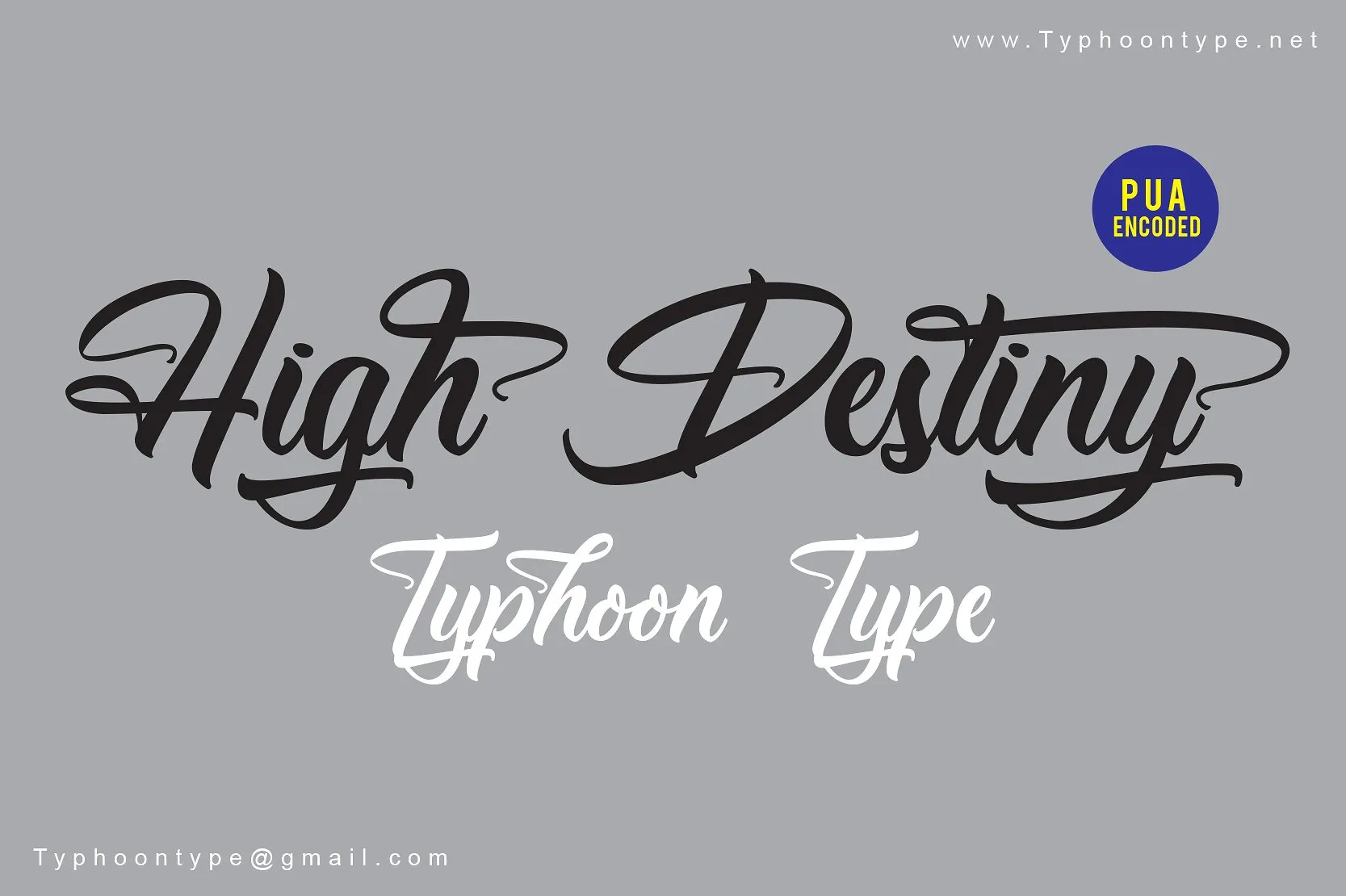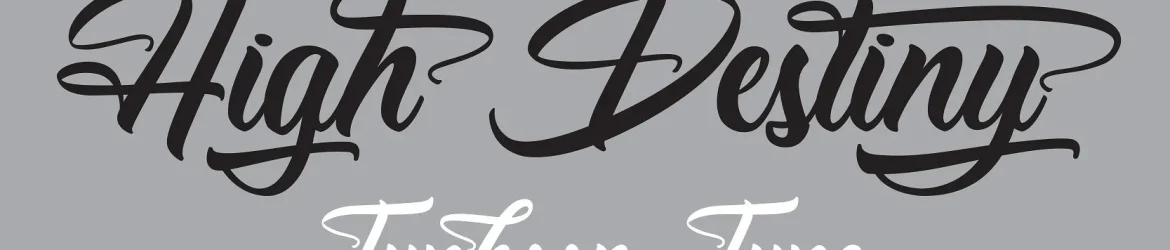
High Destiny Script Font – Download Grátis
Este é uma bela fonte de script calligrafia com um estilo único de bônchô. Introduzimos a High Destiny Fonte! Com uma linha forte e poucos nós, esta tipografia foi cuidadosamente projetada para uso em qualquer software de computador. A High Destiny está perfeitamente adaptada para logotipos, etiquetas de nome, anúncios, embalagens de produto, roupas, mídias sociais e cartões de agradecimento. Este é o tipo de fonte que precisa em sua próxima criação visual. Suavemente elegante com uma atitude brincalhona, ela será uma escolha certa para qualquer projeto onde você deseja destacar seu design personalizado. Essencialmente perfeita para os seus projetos digitais e impressos!